今日は「手書きメッセージの力」についてお話しします🖊️
最近、LINEやメールで済ませがちなメッセージ。
でも、手書きの一言って、それだけで相手の心にスッと残るものなんです💕
💌なぜ「手書き」が印象に残るの?
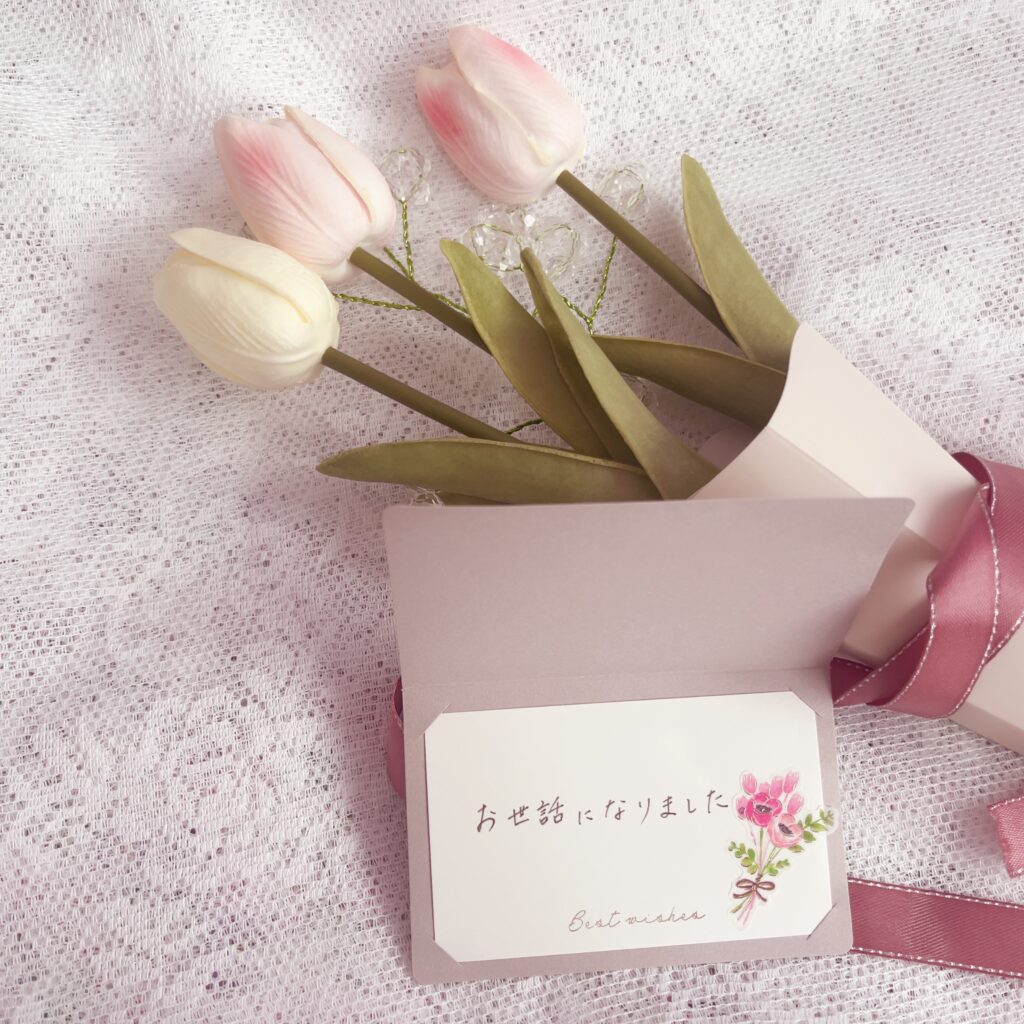
✔️ あなただけの文字には、温かみや個性がある
✔️ 丁寧に書かれた一言は、思いやりが伝わる
✔️ 書くための“時間”そのものがギフトになる
たとえば、仕事でお世話になった方に
「ありがとうございます😊」って一言添えるだけで、「あ、この子ちゃんとしてるな」って 印象アップ間違いなし✨
✨どんな場面で使えるの?
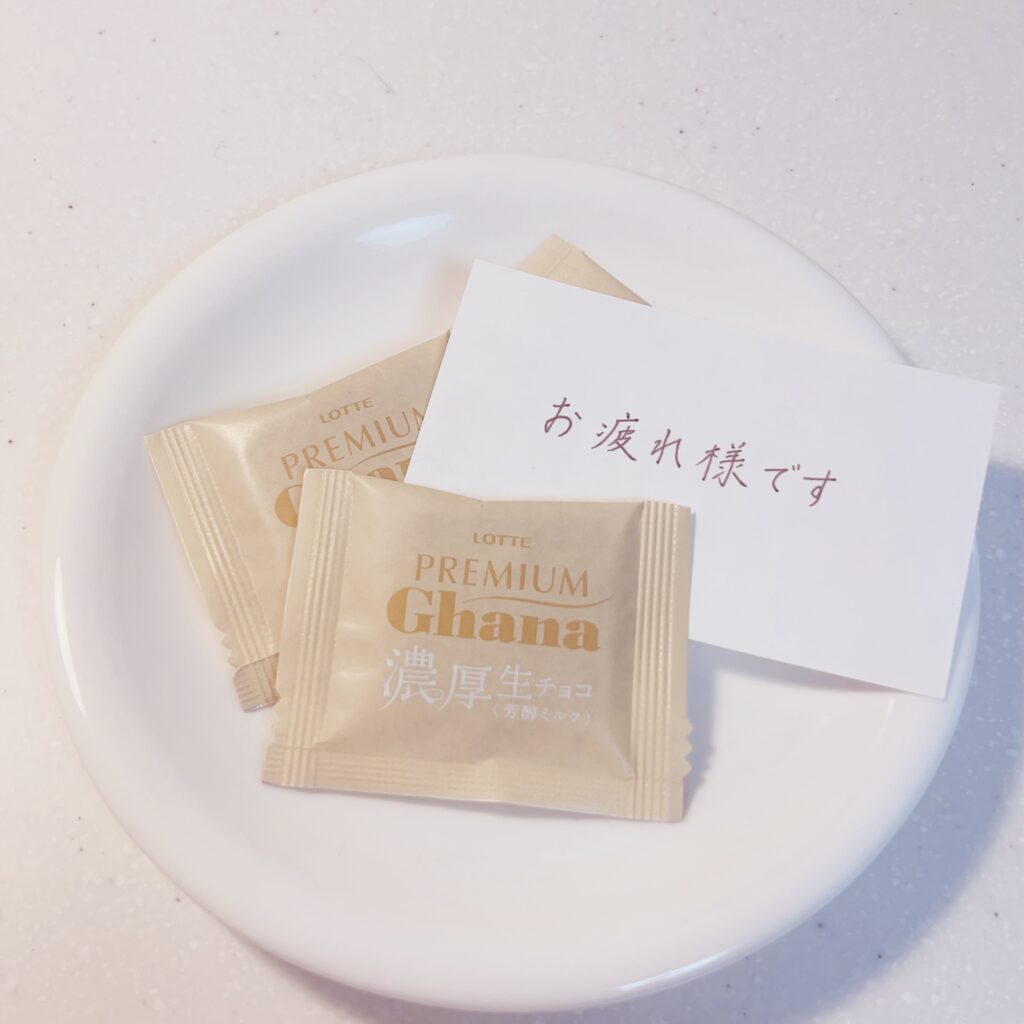
- 書類に一言メモを添える📝
- 送別の色紙やメッセージカードに🌸
- プレゼントに手書きタグやカードを添えて🎁
- ちょっとした差し入れに「おつかれさま♡」のメモ🍪
たったそれだけで、あなたの印象は ぐっと素敵になります💗
🖋おすすめの一言フレーズ集
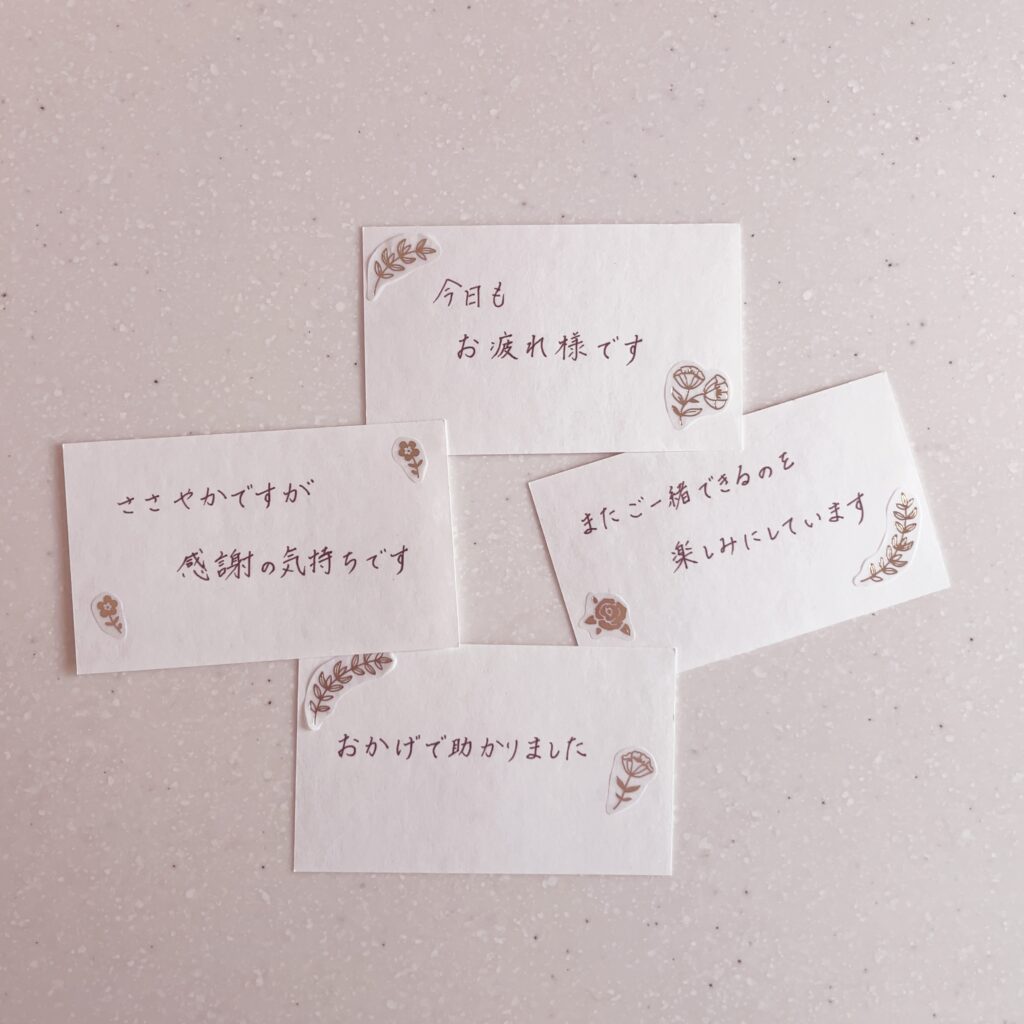
- 「今日もお疲れさまです♡」
- 「おかげで助かりました✨」
- 「またご一緒できるのを楽しみにしています😊」
- 「ささやかですが、感謝の気持ちです🎀」
💡ゆいのワンポイントアドバイス
可愛い便せんやメッセージカードをデスクに常備しておくと◎!
急に書く場面でも、サッと対応できて“できるOL感”UP💼✨
♡まとめ♡
ちょっとした手書きの一言が、
あなたの印象力をグンと引き上げてくれます🕊️
「字がきれい」じゃなくても大丈夫。
心を込めて書くことが一番大事なんです✨